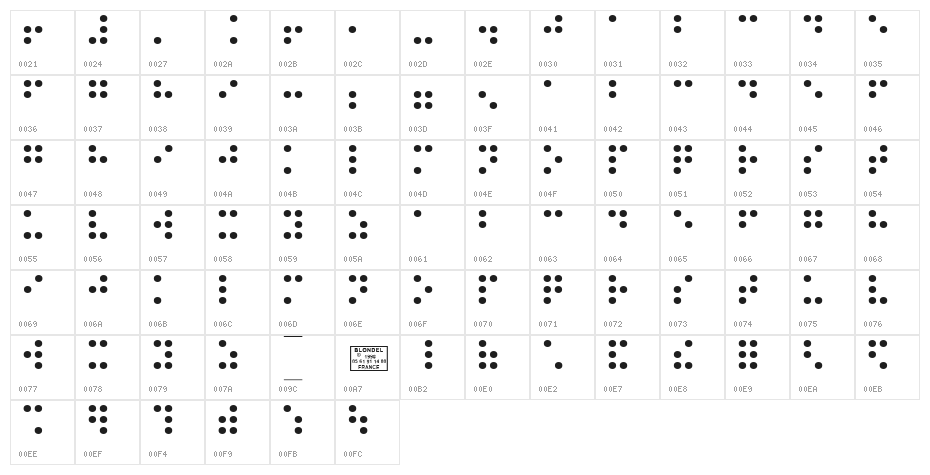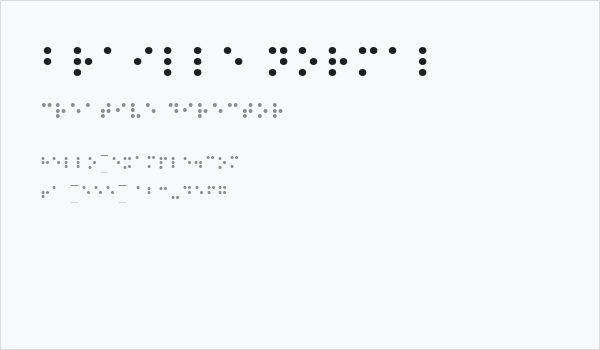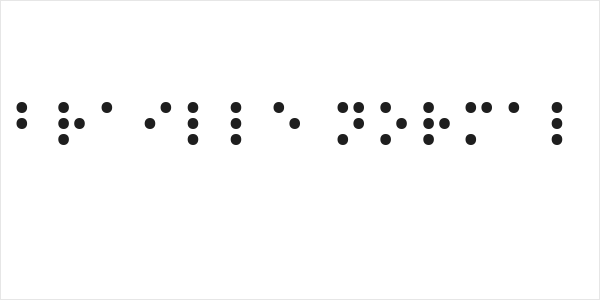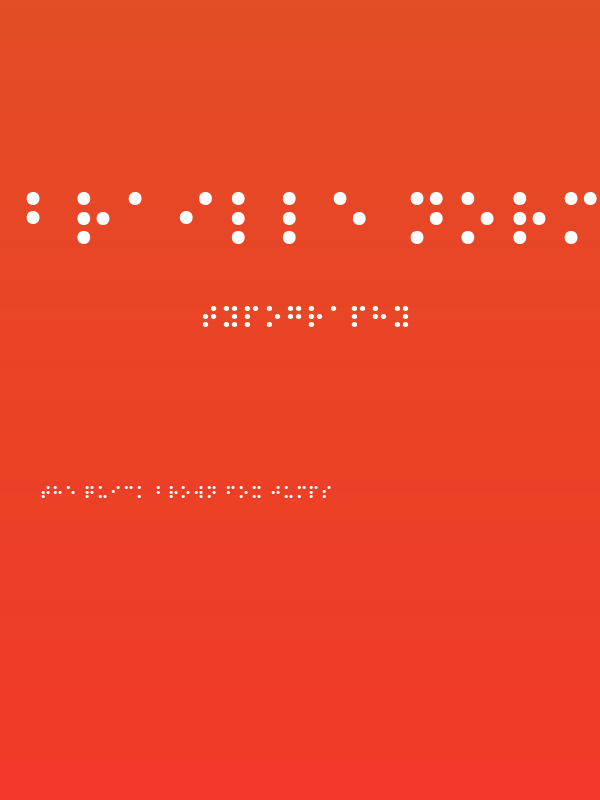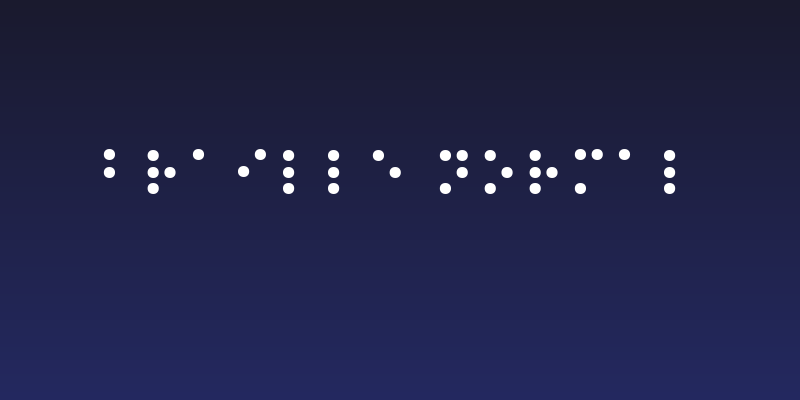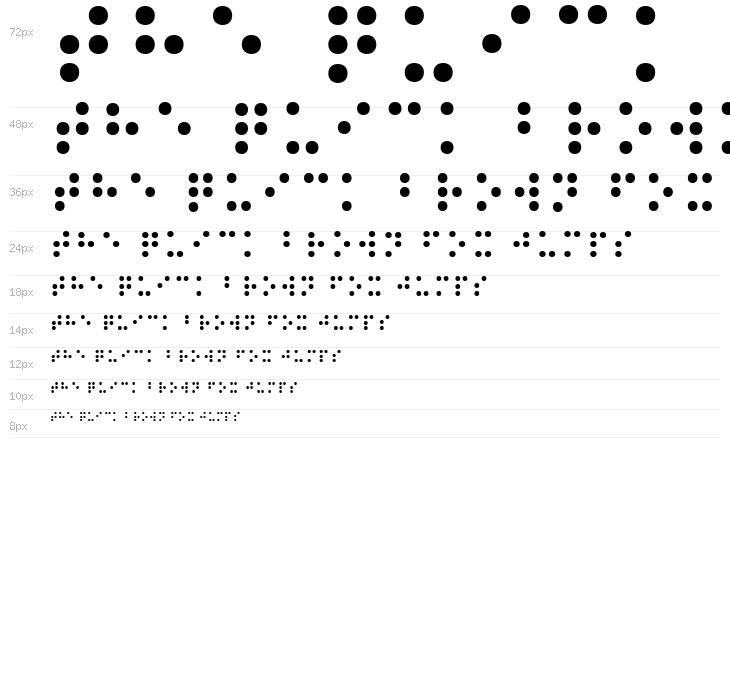
Braille Normal Font
| Stile generale | Functional |
| Caso d'uso | Accessibility, Educational materials, Signage |
| Progetti proposti | Ideal for creating accessible materials, educational tools, and signage for visually impaired individuals. |